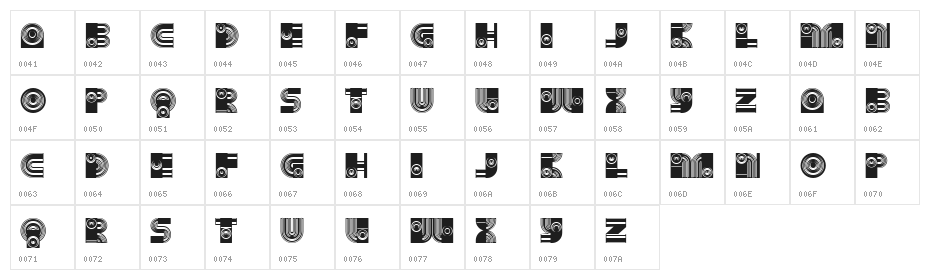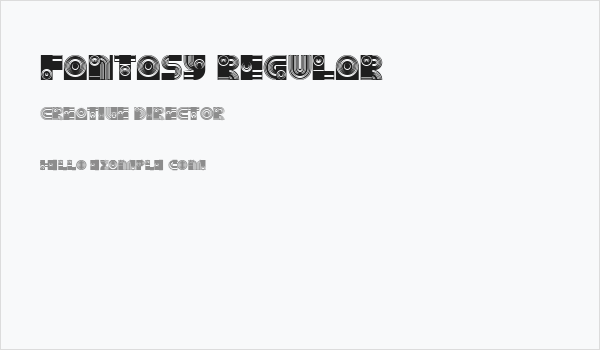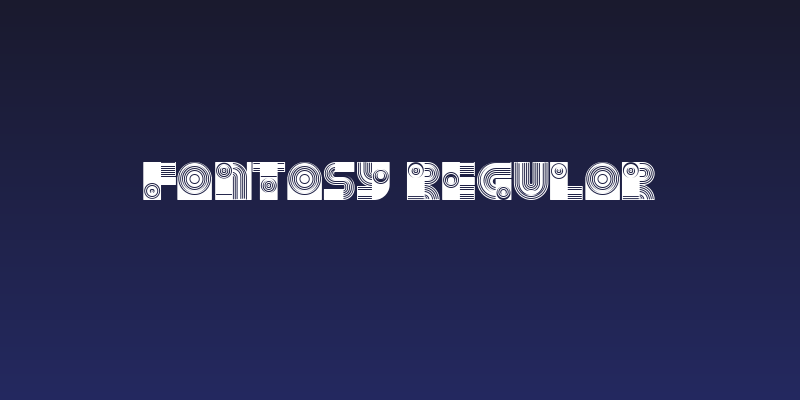
Fantasy Regular Font
| Stil general | Modern, Artistic |
| Proiecte propuse | Ideal for album covers, posters, branding for creative industries, and any project requiring a modern, artistic touch. |